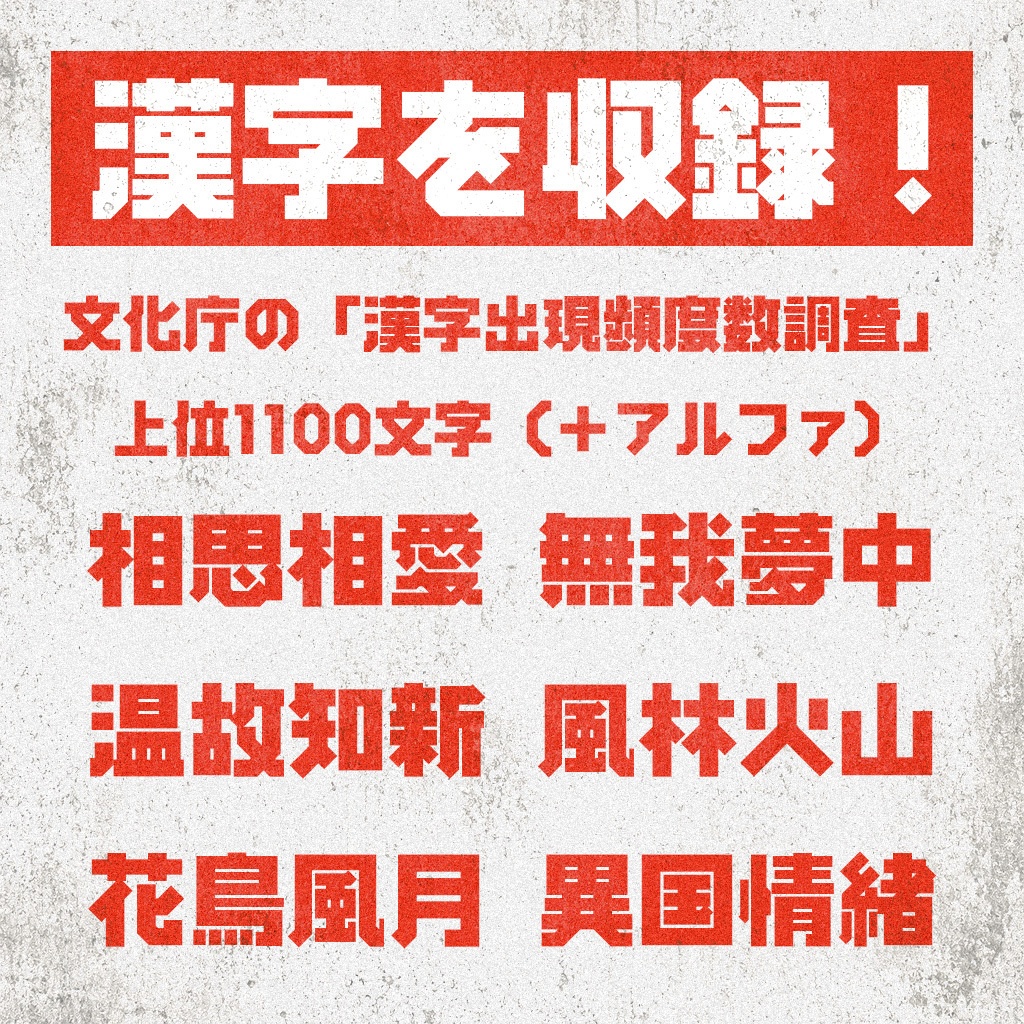
【ver1.1.2】フォント「MiFファイト」
━━━━━━━━━━━━━━━━━━━━━━━━━━━━━━━━━━ ★★ver.1.1.2 公開!★★ ●ver.1.1.2 漢字全体のバランスや形状を改めて確認した上で、気になった部分を個別に調整、半角コロンの点の位置がずれていたのを修正しました。 ●ver.1.1.0 漢字を100字追加しました(頻出漢字の1001~1100位までの範囲)。 丈煙黄曜宣徒届遣訴絡茂採釣批誘核哲豪傾締欠鹿就迷滅仰瀬洗互鼻致伏宝也杉患審才延律希避吾揺甘湾浦沈至販裕更盟欧執崩鬼酸砂尊拡紅漢複歯泊銃荷維盗枝縄詩廃充依鏡幼仮吐慣請晩眺沖斬躍威勇屈勘徹斎謝昇艦寿催舎仁 ━━━━━━━━━━━━━━━━━━━━━━━━━━━━━━━━━━ カクっとした太めの和文フォントです。 通常版はひらがな、カタカナ(全角・半角)、英数字(全角・半角)、一部記号約物、漢字(文化庁の「漢字出現頻度数調査」の上位1100文字)を収録しています。詳しくは「●収録文字」をご覧ください。縦書きに対応した文字も入ってます(通常版のみ)。 ▲フリー版はひらがな、カタカナ(全角)、英数字(半角)、一部記号約物(!?#'(),._、。・!?ー~…()「」)です。 ▲初めてのフォント制作で至らない部分が多々あります。それゆえ修正のアップデートを高頻度で行う場合があります。その点ご理解いただいた上でご利用ください。 ※漢字の追加等のアップデートに伴い、掲載されている価格は予告なく変更される場合がございます。あらかじめご了承ください。 ●フォントについて バージョン:1.1.2 最終更新日:2026年8月15日 ファイル形式:TrueType(.ttf) ●本フォントの利用 通常版・無料版問わず、個人利用はもちろん、商用利用も可能です。 映像や印刷物、同人活動などにご活用いただければ幸いです。 ▲注意点 ロゴへの利用は可能ですが、商標登録は禁止です。 Webフォントとしての利用、およびサーバーへのフォントファイルのアップロードは禁止します。画像化してご利用ください。 アプリやゲームへの埋め込みは、第三者がフォントデータを容易に抽出できない形式(暗号化、難読化など)を講じる場合に限り、することができます。 AI生成物への利用は可能です。しかし、フォントファイル自体の機械学習への利用(LoRA作成等)は禁止します。 ●インストール可能台数 1ユーザーにつきPC・モバイル端末合わせて2台まで利用することができます。 ●その他禁止事項 本フォントを改変・再配布すること。 本フォントを公序良俗に反する目的、特定の個人、団体、人種、信条、性別、社会的身分などを誹謗中傷、差別、攻撃する目的で利用すること。 本フォントファイル自体を無断転売すること。 本フォントの制作者であると偽ること 本フォントファイル自体をNFT化し、取引可能な状態で発行・販売すること。 ●著作権・クレジット表記 本フォントの著作権は、制作者 Mito に帰属します。 クレジット表記は不要です。 ●免責事項 本フォントの入手・利用により発生したいかなる損害・トラブルについても、制作者は一切の責任を負いません。 ●更新履歴 ver.1.1.2 漢字全体のバランスや形状を改めて確認した上で、気になった部分を個別に調整、半角コロンの点の位置がずれていたのを修正 ver.1.1.1 字形調整(海吸仰群祖独脳福毎、「貝」を構成に含む漢字の一部、「毋」を構成に含む漢字の一部) ver.1.1.0 漢字100字を追加、字形調整(県御樹術) ver.1.0.0 リリース ●収録文字(通常版) !"#$%&'()*+,-./0123456789:;<=>?@ABCDEFGHIJKLMNOPQRSTUVWXYZ[\]^_`abcdefghijklmnopqrstuvwxyz{|}~。「」、・ヲァィゥェォャュョッーアイウエオカキクケコサシスセソタチツテトナニヌネノハヒフヘホマミムメモヤユヨラリルレロワン゙゚、。,.・:;?!゛゜〃々〆〇ー―‐/\~|…‥‘’“”()〔〕[]{}〈〉《》「」『』【】+-±×÷=≠<>≦≧∞♂♀°′″℃¥$¢£%#&*@○●◎◇◆□■※→←↑↓≒♪◯0123456789ABCDEFGHIJKLMNOPQRSTUVWXYZabcdefghijklmnopqrstuvwxyzぁあぃいぅうぇえぉおかがきぎくぐけげこごさざしじすずせぜそぞただちぢっつづてでとどなにぬねのはばぱひびぴふぶぷへべぺほぼぽまみむめもゃやゅゆょよらりるれろゎわゐゑをんァアィイゥウェエォオカガキギクグケゲコゴサザシジスズセゼソゾタダチヂッツヅテデトドナニヌネノハバパヒビピフブプヘベペホボポマミムメモャヤュユョヨラリルレロヮワヰヱヲンヴヵヶ①②③④⑤⑥⑦⑧⑨⑩⑪⑫⑬⑭⑮⑯⑰⑱⑲⑳≒阿愛悪握圧安暗案以伊位依囲委威意易為異移維衣違遺医井域育一印員因引飲院陰隠右宇羽雨浦云運雲営影映栄永英衛益駅越円園延援演煙縁遠央奥応押横欧王黄岡沖億屋憶俺温音下化仮何価加可夏家科果歌河火花荷華課過我画賀介会解回壊快改海界絵開階外害街各拡格核確覚角閣革学楽額掛割活株刊勘巻完官幹患感慣換漢環甘監管簡艦観間関韓館丸含岸眼岩顔願企危喜器基奇寄希期機帰気紀規記貴起鬼儀技疑義議吉詰客逆久休及吸宮急救求泣球究級給旧去居巨拠挙許魚京供競共協叫境強恐教橋況胸興郷鏡響驚仰業局曲極玉勤禁筋近金銀九句区苦駆具空屈繰君群軍係傾刑兄型形恵携景系経継計警軽芸迎劇撃激欠決結血月件健剣嫌建憲検権犬研県肩見遣険験元原厳減源玄現言限個古呼固己庫戸故五互午吾後御語護交候光公功効厚口向好工幸広康抗攻更校構江港甲皇紅考航荒行講降香高号合豪刻告国黒腰骨込頃今困婚根混佐左差査砂座催再最妻才採歳済斎細裁載際在材罪財坂阪崎作昨策察撮殺雑三参山散産算酸斬残仕使刺司史四士始姉姿子市師志思指支施枝止死氏私紙至視詩試誌資歯事似児字寺持時次治示耳自辞鹿式識七執失室質実舎写射捨社者謝車借若弱主取守手種酒首受寿授樹収周宗就州修秀秋終習衆襲週集住充十従重銃宿出術述春瞬準純順処初所緒書諸助女除傷勝商将小少床承昇昭松消焼照症省称章笑紹証象賞障上丈乗城場常情条状植織職色触食伸信寝審心振新森深申真神臣親身進震人仁訊陣図吹推水数杉世瀬制勢性成政整星晴正清生盛精聖声製西請青静税席昔石積責赤跡切接折設節説雪絶先千占宣専川戦泉浅洗染線船選鮮前善然全祖素組訴創倉層想捜操早争相窓総草装走送騒像増蔵造側則息束測足速属族続存孫尊村他多太打体対帯待態替退隊代台大第題宅沢達脱谷誰単担探短端団弾断段男談値知地智池置致遅築竹茶着中仲忠昼注著丁庁張徴朝町眺聴調超長鳥直沈津追痛通釣低定帝底庭弟提程締敵的適哲徹鉄典天展店転点伝殿田電吐徒渡登途都度土怒倒党冬刀島投東盗湯当等答統藤討踏逃頭闘働動同堂導道得徳特督独読突届奈那内縄南難二肉日乳入任認熱年念之濃納能脳農波派破馬廃敗背配倍買売博泊白薄迫爆八発髪抜判半反板版犯般藩販飯晩番否彼悲批比皮秘被費避非飛備尾微美鼻彦必筆百標表評描病品浜頻不付夫婦富布府怖敷普浮父負武舞部風伏復服福腹複払仏物分文聞兵平柄並閉米壁別変片編辺返便弁保捕歩補暮母包報奉宝崩抱放方法訪豊亡忘房暴望防北僕堀本魔麻枚毎幕末万満味未密妙民眠務夢無娘名命明盟迷鳴滅面模茂毛木黙目戻問門也夜野弥矢役約薬訳躍柳油輸優勇友有由裕誘遊雄融夕予余与幼容揺曜様洋用葉要陽養欲翌来頼絡落乱利理裏里離陸律率立略流留旅両料療良量領力林輪隣類令例冷礼齢歴列恋練連路露労老郎六録論和話惑湾腕 ●お問い合わせ 不具合等がありましたら、BOOTHのメッセージからお願いします。 利用規約はたぬき侍様の「フォント利用規約ジェネレーター」(https://tanukifont.com/license-gen/)を参考に制定しました。